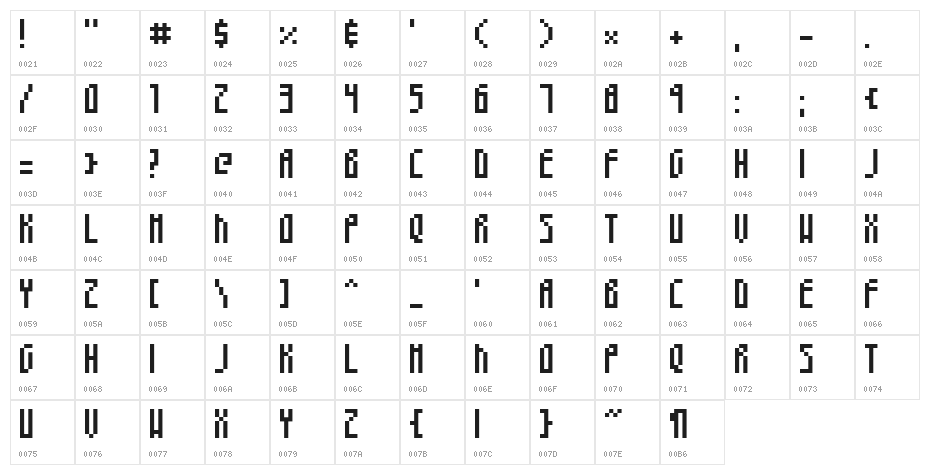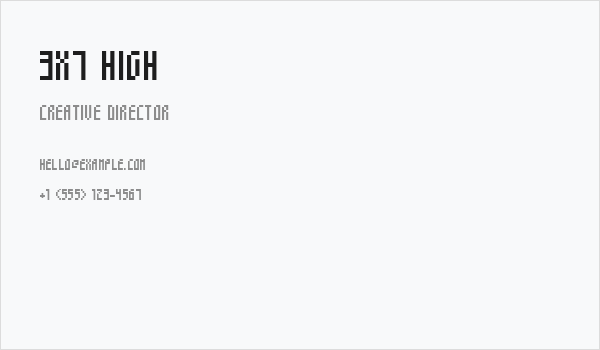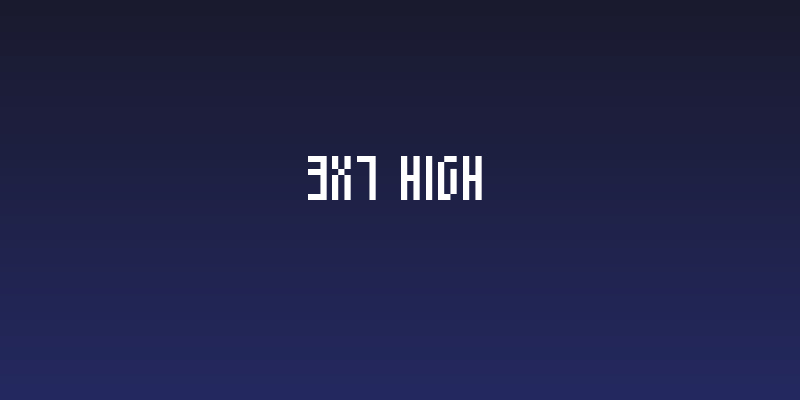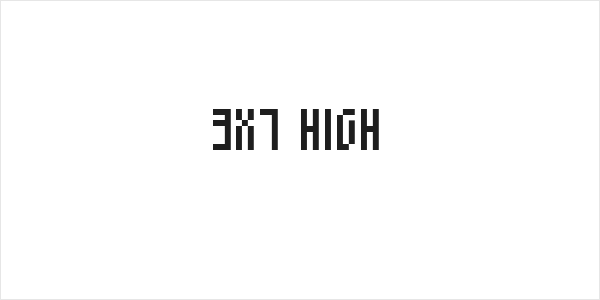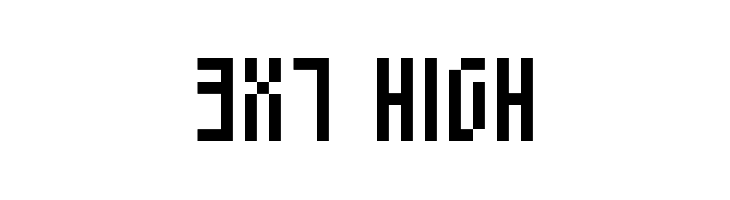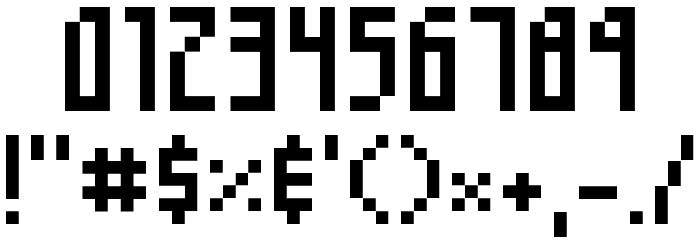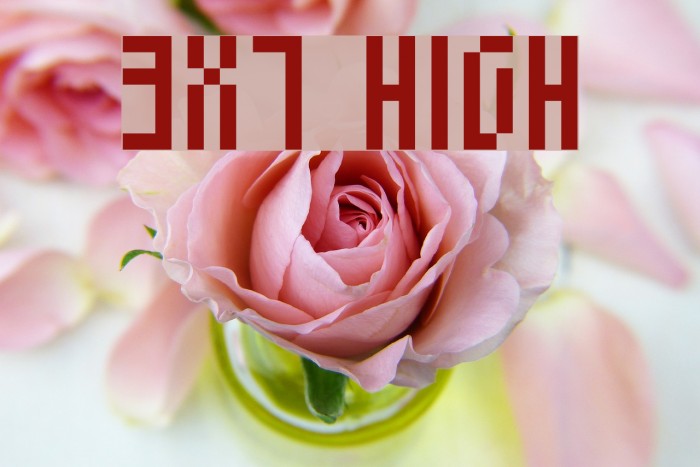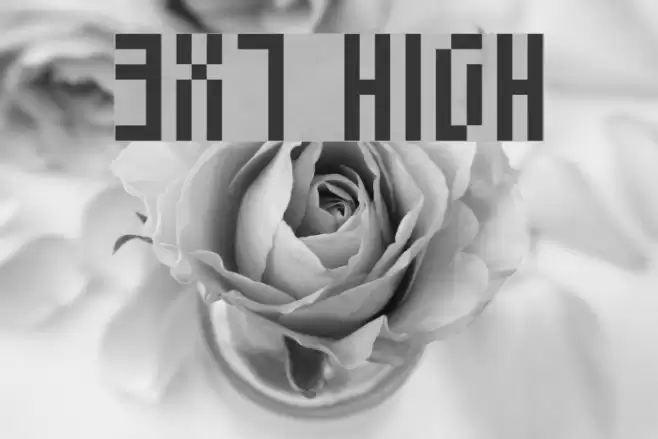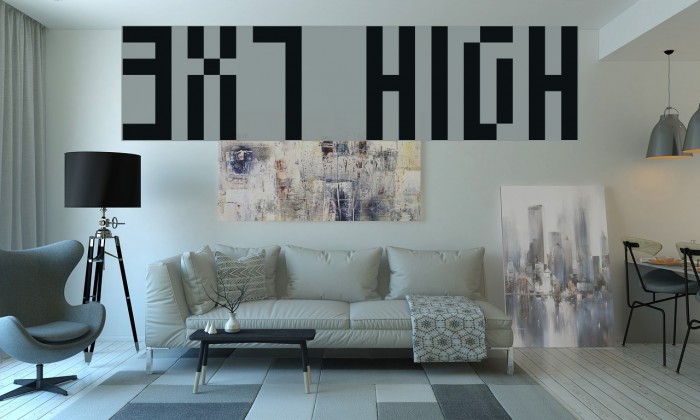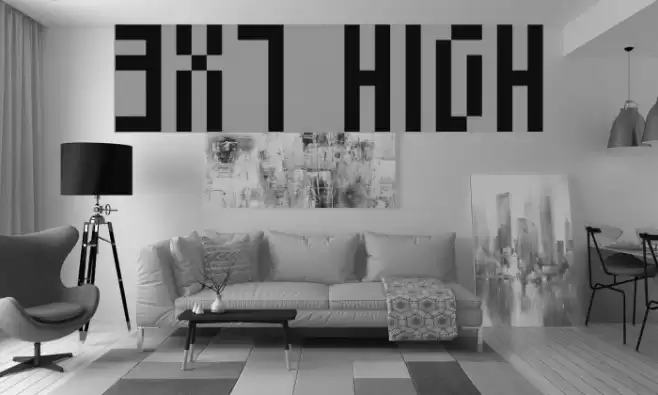
3x7 High Font
| Caz de utilizare | Headlines, Logos, Digital Art |
| Proiecte propuse | Ideal for retro video game designs, tech-themed posters, digital art projects, and any creative work that seeks to evoke a sense of nostalgia for early computing. |